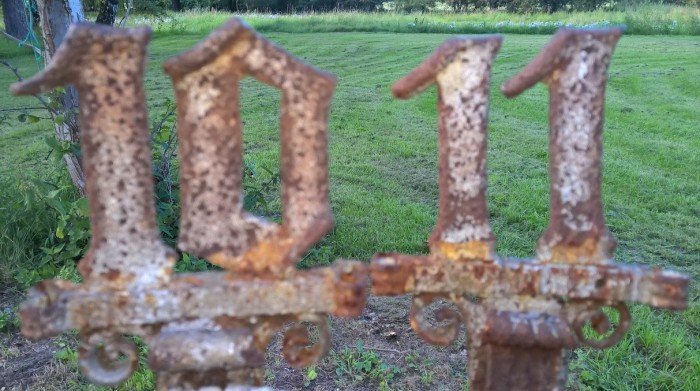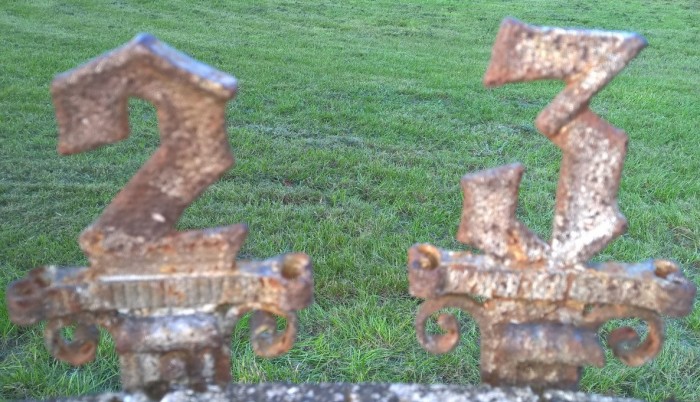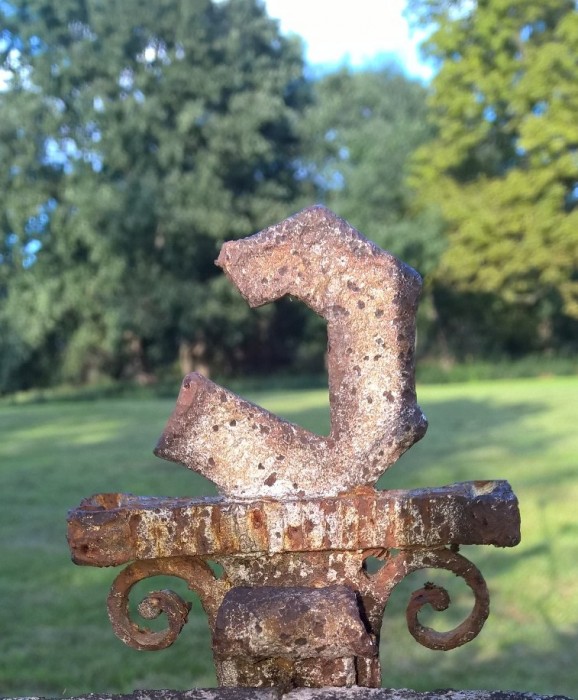
Schmiedeeiserne Ziffern einer historischen Sonnenuhr restaurieren = Welche Schrift?
ein befreundeter Kunstschmied ist an mich herangetreten mit einer Bitte: Eine historische Uhr soll restauriert werden. Die Ziffern sind stark vom Rost beschädigt, es gibt nur noch die auf den beigefügten Fotos (s. u.).
Der Kunstschmied sieht sich außer Stande, die fehlenden Zahlen ohne Vorlage zu ersetzen. Auf den Fotos seht Ihr die noch vorhandenen Ziffern 10, 11, 2, 3 und einen Teil der 5. Die Ziffern müssten von 1 bis 12 gegangen sein, und ich soll nunr Vorlagen erstellen.
Welche Schrift wurde hier wohl als Ausgangsschrift genommen, oder welche könnte man nehmen, um daraus Vorlagen für den verschwundenen Rest zu machen?
Die sollte man einen Graphiker / Typographen zeichnen lassen. Der kann die Formensprache aufnehmen und die restlichen Ziffern so entwerfen, daß sich ein schlüssiges Gesamtbild ergibt. Bei der Gelegenheit kann er vielleicht auch optische Unstimmigkeiten der Vorlage glätten (die 2 sieht mir etwas verkorkst aus). Das erfordert einiges an Erfahrung und Fingerspitzengefühl. Wenn die Aufgabenstellung lautet, möglichst nahe an der vorhandenen Substanz zu bleiben und trotzdem am Ende ein stimmiges Gesamtbild zu haben, wird eine fertige Schrift hier vermutlich nicht die beste Lösung sein.
Gebrochene Ziffern wirst du kaum finden. Ziffern haben eine andere Herkunft als Buchstaben, sie sind in keiner der gebrochenen Schriften, sei es Gotische oder Fraktur (Rotunda und Schwabacher sowieso nicht) mitgebrochen worden. Allenfalls in Ausnahmen. Ich würde vermuten, daß in den deutschnationalen Entgleisungen wie Tannenberg, Element, Potsdam, Gotenburg und solchen Kreaturen die totale Bruchwut vielleicht vor den Ziffern nicht haltgemacht haben könnte. Aber gute gebrochene Schriften haben keine vollständig gebrochenen Ziffern. Die 3 ist ein besonders monströses Exemplar. Die 2 stimmt schreibtechnisch nicht. Du kannst versuchen, eine Breitfeder dieser 2 nachzuführen, es wird ohne Verrenkungen nicht gehen. Die 0 hat auf ihrer rechten Seite entweder ein ordentliches Stück verloren oder ist von vornherein mißraten. Sie läßt sich ganz gut mit den Buchstaben »O, o« vergleichen. Man wird sehen, daß die Strichführung nicht stimmen kann. Also: Was wir da sehen, sind Ungetüme, schlecht gemachte Zeichen. Es gab wahrscheinlich keine geschriebenen Vorlagen, sondern aus dem Gedächtnis und laienhaft gezeichnete, bei denen auch die Befestigungsmöglichkeit in die Figur einbezogen wurde. Die sitzen ja recht ungraziös. Wenn man das wiederherstellen möchte, müßte man es mit dieser Haltung der Urheber tun. Also Ziffern so eigentümlich brechen, vielleicht nach Vorlagen der o.g. Primitivgotischen. Mit Kalligrafie ist der Sache nicht beizukommen, weil die Zeichen eben nicht geschrieben sind, sondern untypisch konstruiert und gezeichnet. Eine echte Rekonstruktion wird hier verlangt.
Wenn es Abweichungen geben darf, einfach die Gotischen, vor allem die nationalistischen durchsehen (wobei man dann etwas ungraziöses und historisch belastetes zitiert), und wenn es schön werden darf, ganz neu ansetzen und Kriterien dafür entwickeln. Vielleicht kann auch ein Schriftkünstler aus den hier so häßlich wirkenden Ungeschicklichkeiten etwas Schönes zaubern.
Die o. gez. Zahlen sind so historisch überhaupt nicht „korrekt"? Habe ich das richtig verstanden: Es gibt historisch keine gebrochenen Zahlen in Fraktur-Schriftsätzen?
@Schröder - Zitat: „Ziffern haben eine andere Herkunft als Buchstaben, sie sind in keiner der gebrochenen Schriften, sei es Gotische oder Fraktur (Rotunda und Schwabacher sowieso nicht) mitgebrochen worden.“
Wie ist das historisch zu erklären? Gibts dafür bekannte Gründe?
Das erklährt sich wohl aus der Herkunft der gebrochenen Schriften, die ja im wesentlichen aus den Kloster-Schribstuben stammen, wo eine gut mit dem Federkiel schreibbare, und leicht, auch von nicht unbedingt talentierten Schreibern gut erlernbare, sehr normierte Schrift erforderlich war, um so im wesentlichen Bibeln in größerer Zahl abschreiben zu können. Hier spielten die arabischen Ziffern praktisch keine Rolle. Zu dieser Zeit waren die römischen Ziffern - aus Buchstaben einfach die gängige Ziffernart.
Die (indisch-)arabischen Ziffern kaben aber eher über Händler und Geldverleiher in unsere Kultur, und die schriftlichen Zeugnisse hier waren eben nicht in der strengen gebrochenen Schrift verfasst, sondern in Kurrentschrift, und brachten von hier ihre runden Formen auch mit in die Druckschrift.
Typische Fraktur-Ziffern sehen daher etwa so aus:
Erst in den 1930er Jahren, in denen die oft "Schaftstiefel-Fraktur" genannte Schrift auf kam, wurden dann vielerorts auch Ziffern in diese eckige Form gebracht, oft ohne Rücksicht darauf, ob sich diese überhaupt derart schreiben liassen, benutzt man eine Breitfeder. Manche der Tannenberg-Clones, die dann  praktisch jede Schriftgießerei heraus brachte hatten dann auch derart ge- oder verbrochene Ziffern.
Ich lese hier eigentlich nur (mäßig :-?) interessiert mit, aber eins hat mich überrascht: es soll vor den Schaftstiefelgrotesken gar keine gebrochenen Ziffern gegeben haben? Gibt es keine Beispiele von vor, sagen wir mal, 1924? Nicht unbedingt von hoch angesehenen Schriftentwicklern, sondern eben von Kirchturmuhrherstellern oder eben von Leuten, die sich ihre Hausnummer ans Hoftor nagelten? Das hätte ich, ganz naiv, eigentlich nicht erwartet.
Nun, Kirchturmuhrzifferblatthersteller haben zumeist ohnehin römische Ziffern verwendet, und Leute, die Ziffern ans Hoftor nageln, haben ohnehin gemacht, was sie wollten, sofern sie sich ihre Hausnummern selbst schnitzten, nur wurde das dann kaum als Schrift veröffentlicht.
die frage ist natürlich was man alles zu den neugotischen schriften zählt, ist eine wiking (trennert) schon neugotisch?
... und ich bin mir sicher es gibt noch frühere entwürfe ...
Sicher. Zum Beispiel die Black No 284.
Benj. Woods & Co., Novelty Printing Press, Boston, 1875
Als Anglo-Gothic von MacKellar, Smiths & Jordan,
Philadelphia, angeboten.